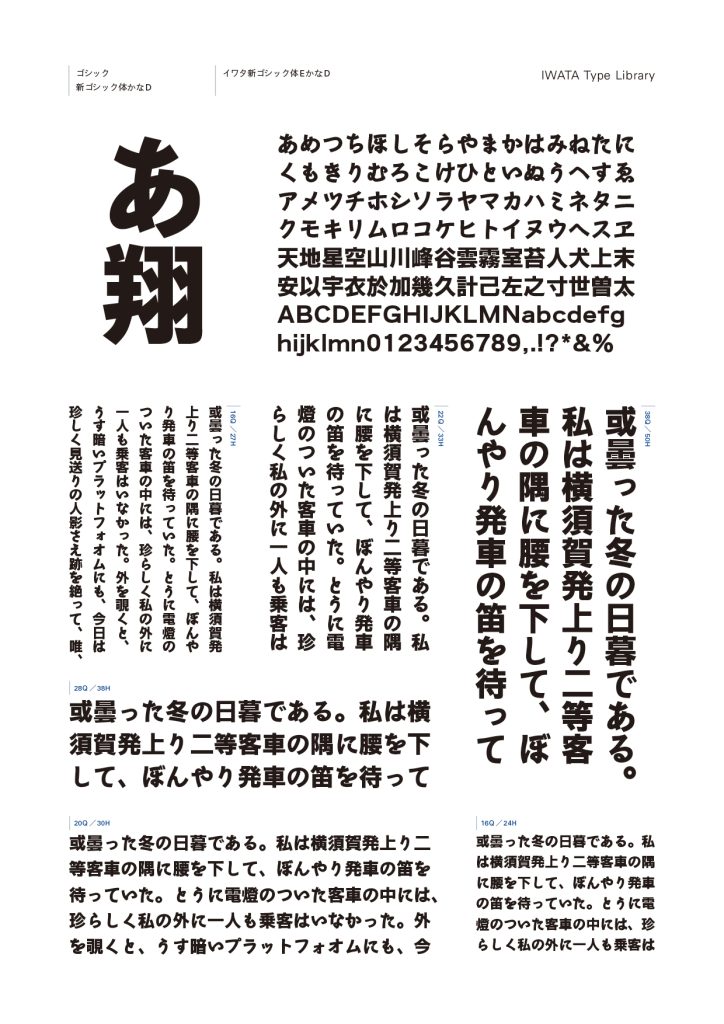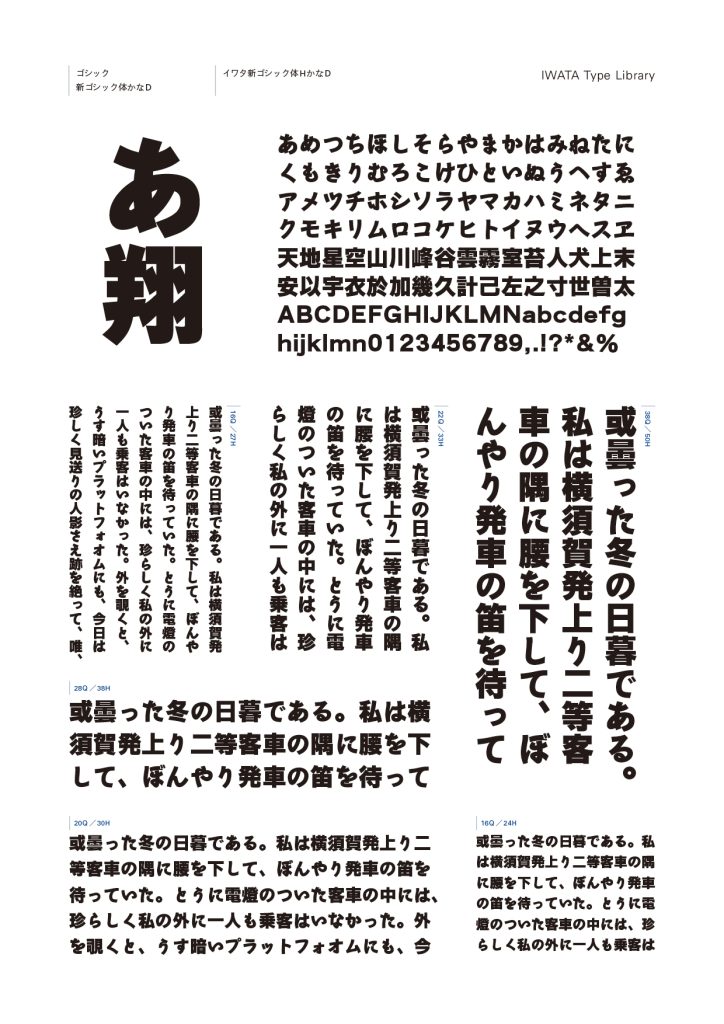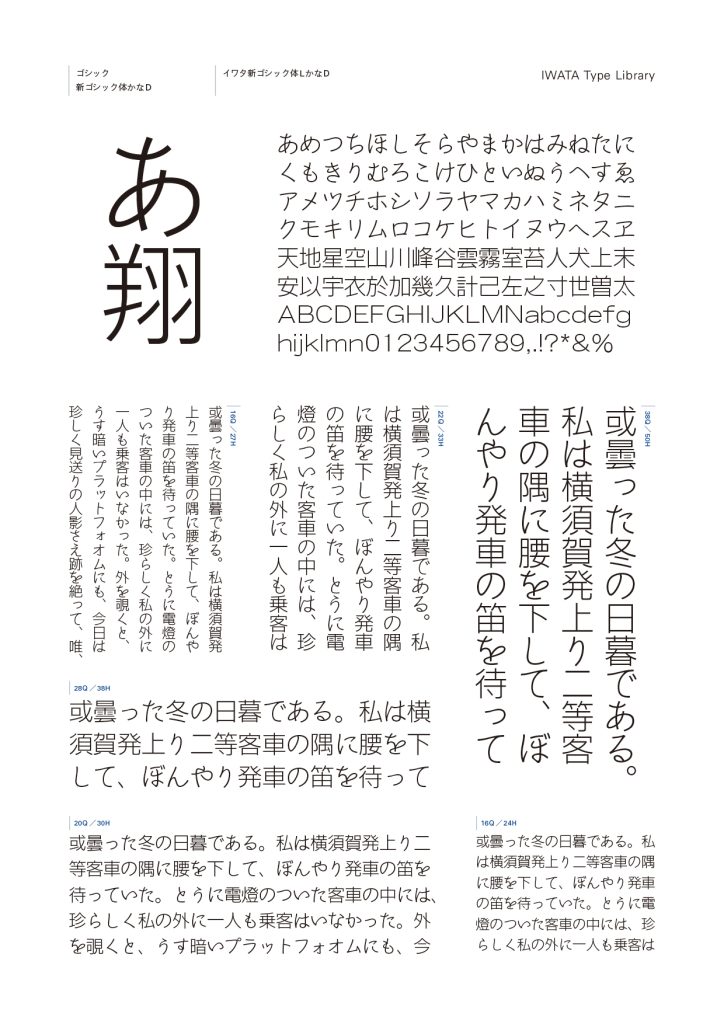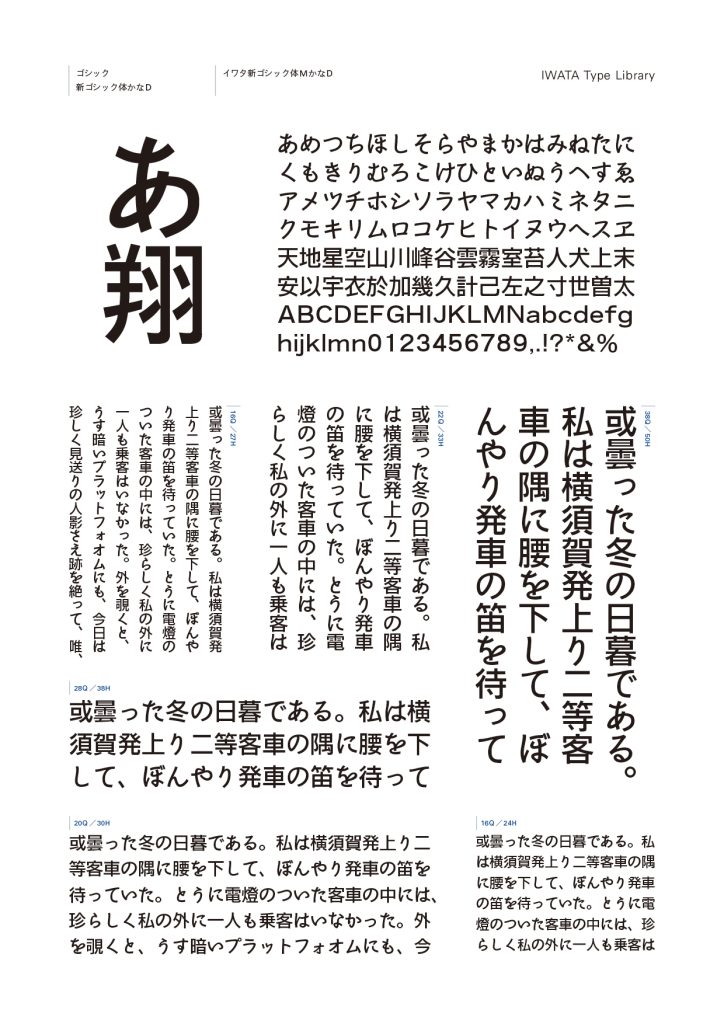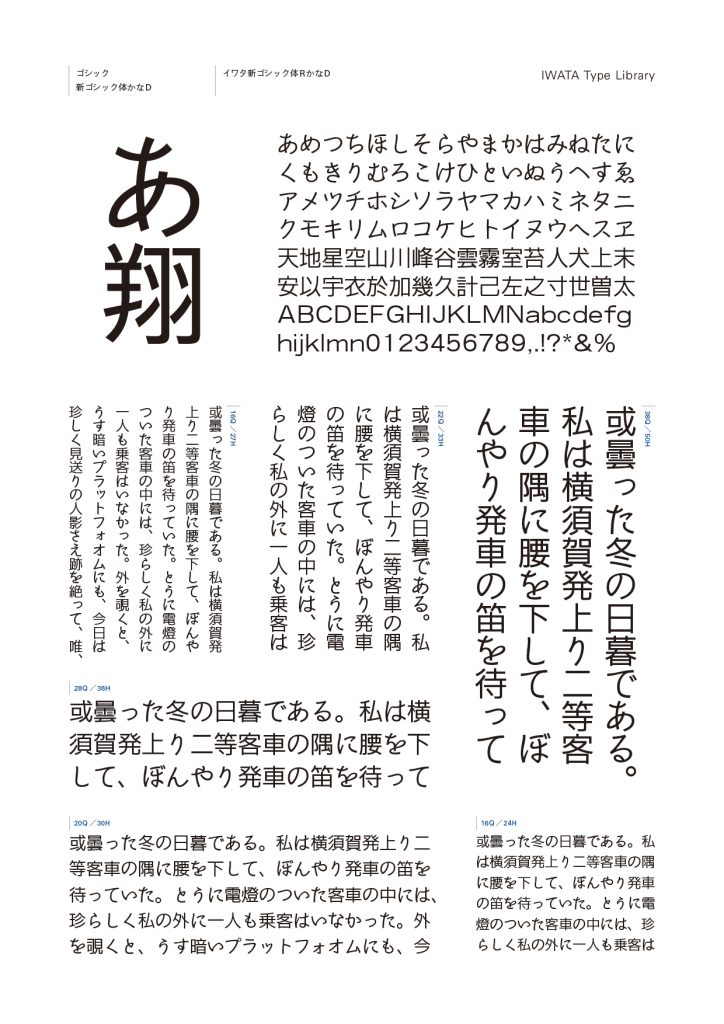
新ゴシック体かなD
イワタ新ゴシック体MかなD
イワタ新ゴシック体LかなD
イワタ新ゴシック体RかなD
イワタ新ゴシック体BかなD
イワタ新ゴシック体EかなD
イワタ新ゴシック体HかなD
イワタ新ゴシック体UかなD
字高・字幅を大きく使ったシャープで現代的なデザインのイワタ新ゴシック体のかなファミリー書体です。
点画を繋げた手書き感の強いデザインです。